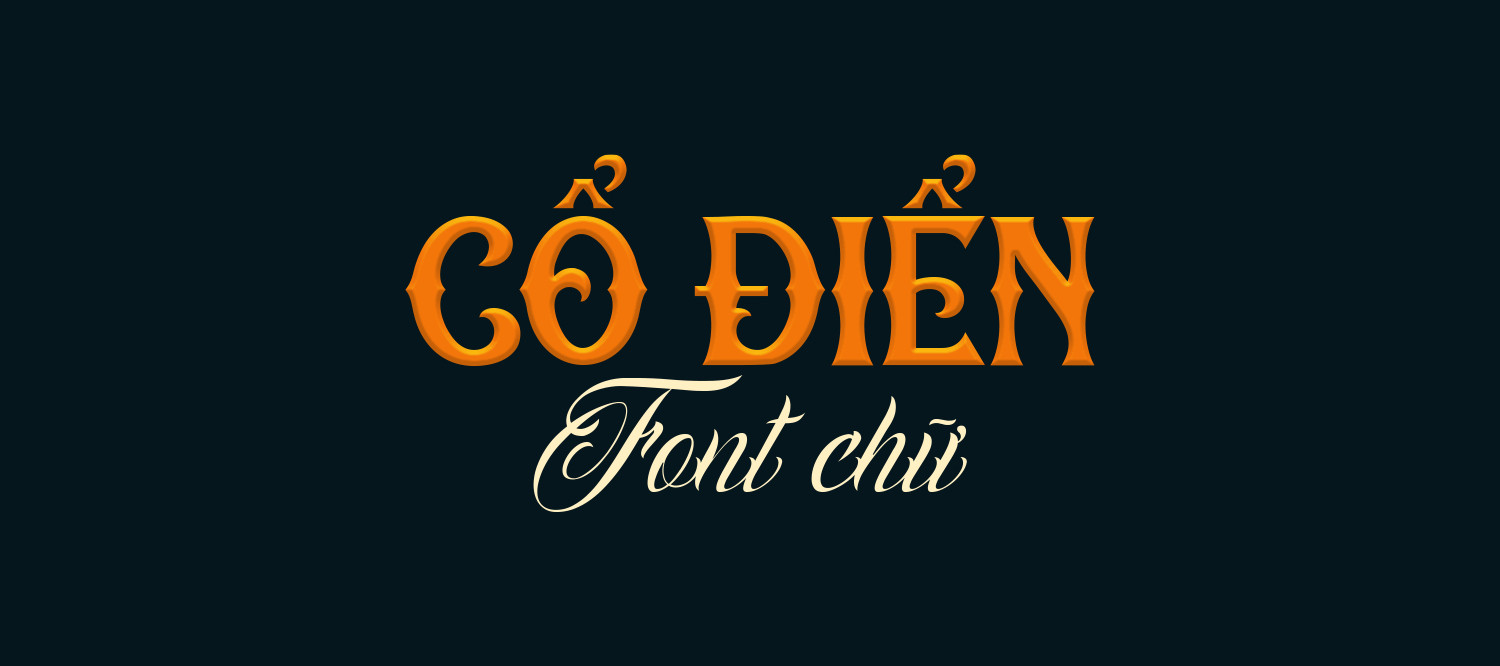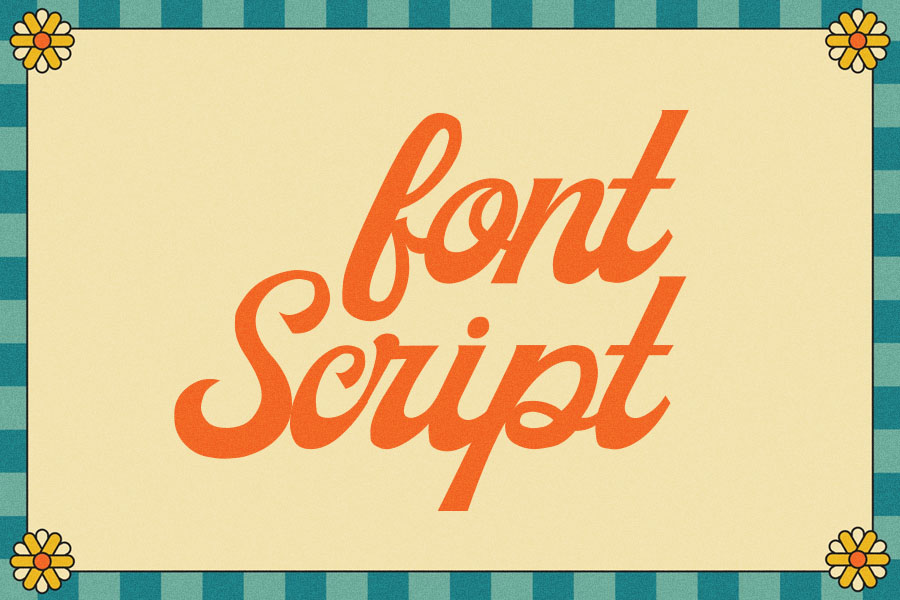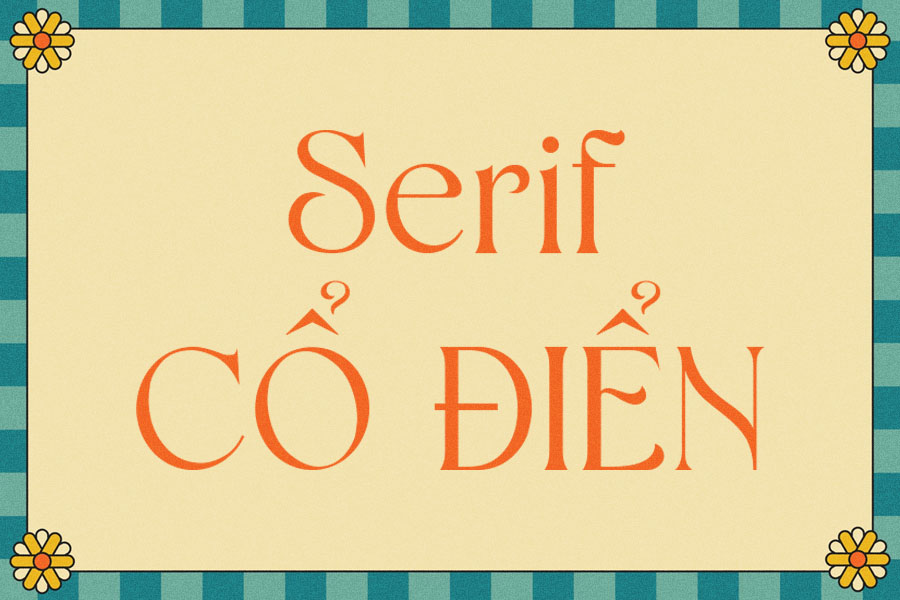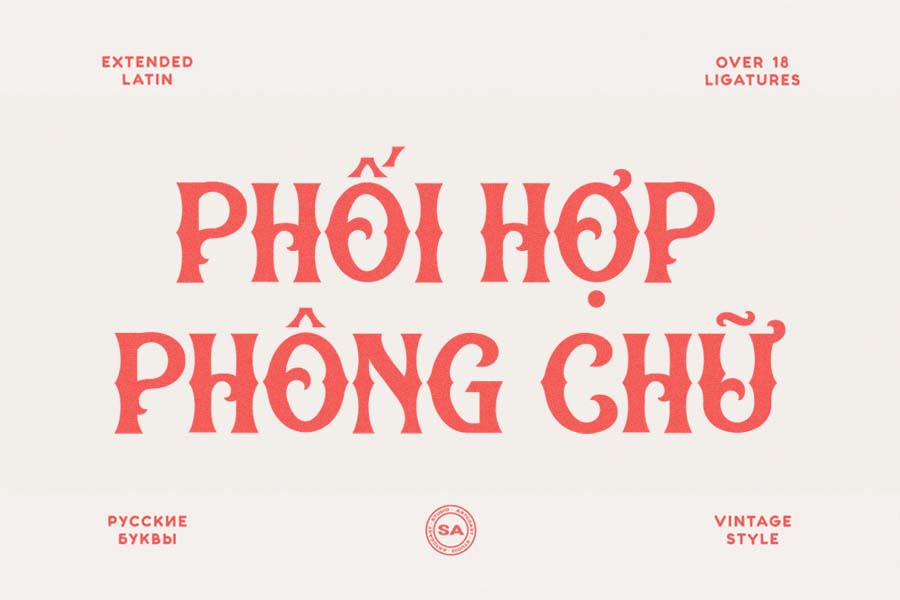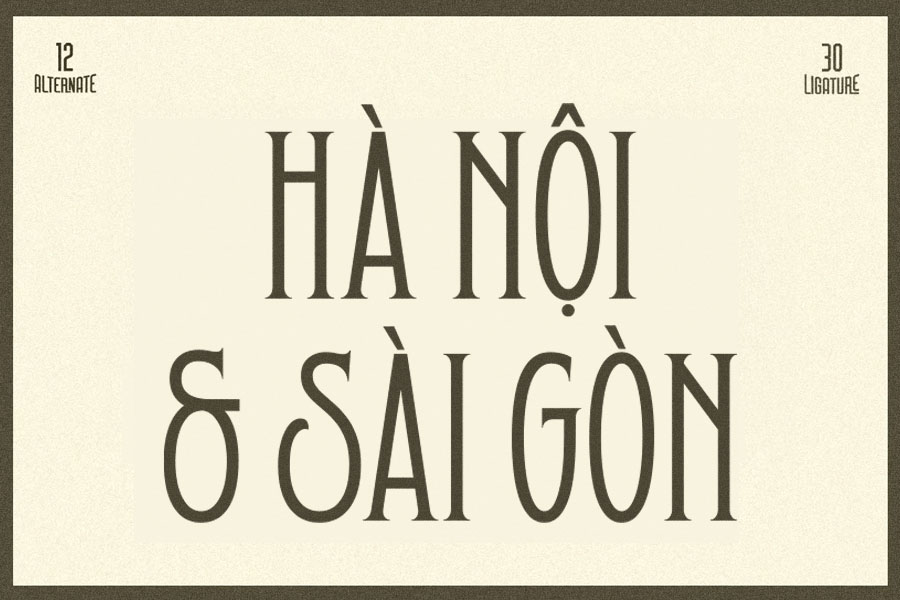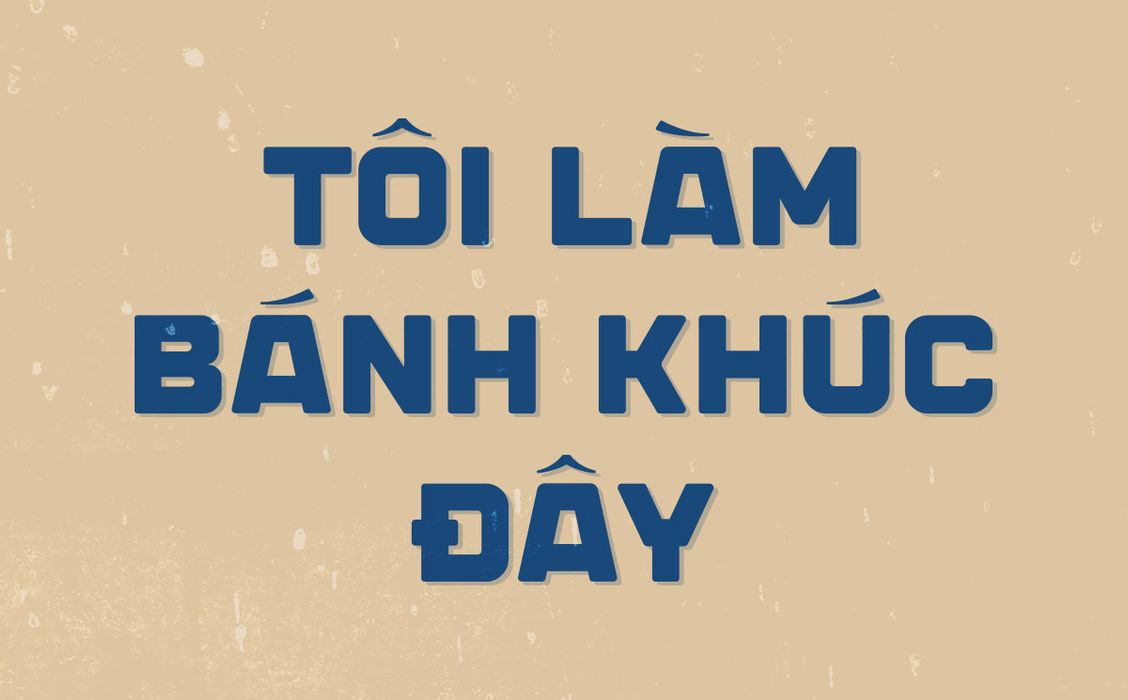
Bạn đang tìm kiếm những kiểu font chữ mang vẻ đẹp vượt thời gian, đậm chất hoài cổ, phù hợp cho các thiết kế logo, poster hay thiệp cưới mang phong cách sang trọng? Font chữ cổ điển chính là lựa chọn lý tưởng – không chỉ tạo chiều sâu cảm xúc mà còn giúp thiết kế nổi bật với phong cách đặc trưng.
Bài viết này sẽ giới thiệu 20 font chữ cổ điển Việt hóa đẹp nhất 2025, phân tích ứng dụng, định nghĩa rõ ràng các phong cách font cổ điển và hướng dẫn cách kết hợp tối ưu – giúp bạn sử dụng đúng font cho từng dự án sáng tạo.
Font chữ cổ điển (classic fonts) là những kiểu chữ mang đậm hơi thở truyền thống, được xây dựng dựa trên các nguyên tắc thiết kế kinh điển, thường xuất hiện trong các ấn phẩm in ấn, biển hiệu xưa hay logo thương hiệu lâu đời. Đặc điểm nổi bật của các font này là đường nét tinh tế, thanh lịch và mang đến cảm giác trang trọng. Một số font có chân (serif) rõ ràng, trong khi số khác mô phỏng nét viết tay mềm mại của thư pháp. Tỷ lệ chữ trong các font cổ điển thường được thiết kế cân đối, tạo nên cảm giác hài hòa, dễ đọc và dễ ghi nhớ. Khi nhìn vào một font cổ điển, người xem thường cảm nhận được nét trang nhã, hoài niệm – gợi nhớ về những thập niên đã qua, từ những năm 50–80 của thế kỷ trước.
Font cổ điển, retro và vintage là ba khái niệm thường bị nhầm lẫn vì đều mang sắc thái hoài cổ, nhưng thực tế mỗi loại lại mang một tinh thần thiết kế riêng biệt.
Font cổ điển (Classic fonts) mang phong cách tinh tế, thanh lịch, thường trung tính và có tính chuẩn mực cao. Những font này thường được dùng trong thiết kế sách, tạp chí, logo của các thương hiệu cao cấp hoặc các ấn phẩm mang tính trí tuệ và trang trọng.
Font retro lại thể hiện cá tính mạnh mẽ và vui tươi hơn. Chúng thường gợi nhớ đến các thiết kế mang âm hưởng của thập niên 70–90, với các đường nét nổi bật, màu sắc bắt mắt và cách điệu có phần nghịch ngợm, trẻ trung. Retro thường được ứng dụng nhiều trong các poster, biển hiệu hoặc thiết kế mang hơi hướng đại chúng và quảng cáo.
Font vintage là sự mô phỏng phong cách xưa cũ một cách rõ ràng hơn, đặc biệt tập trung vào cảm giác sờn cũ, thời gian mài mòn. Chúng thường xuất hiện trong các thiết kế lấy cảm hứng từ thời kỳ bao cấp, tem phiếu, biển hiệu quán ăn xưa hoặc các sản phẩm mang chất dân gian truyền thống. Vintage thiên về chất cảm xúc và chất liệu thị giác cũ kỹ hơn so với retro và classic.
Font serif cổ điển là kiểu chữ có chân (serif), tức là mỗi ký tự đều có những nét kéo dài nhỏ ở đầu hoặc chân chữ. Đây là dạng font phổ biến trong các ấn phẩm cổ điển như sách in, tạp chí, báo chí thời xưa bởi sự dễ đọc, nhịp điệu ổn định và vẻ ngoài trang trọng, trí tuệ.
Font script cổ điển lấy cảm hứng từ chữ viết tay bằng bút máy hoặc thư pháp. Các ký tự thường nối liền nhau, tạo dòng chảy mượt mà và giàu cảm xúc thị giác. Đây là lựa chọn hàng đầu trong các thiết kế cần sự nhẹ nhàng, tình cảm và mang hơi hướng cá nhân.
Font retro và vintage là dòng font mô phỏng lại các kiểu chữ từ thập niên 50–90 hoặc thậm chí thời bao cấp ở Việt Nam. Chúng thường mang vẻ ngoài thô ráp, sờn cũ hoặc có các chi tiết thiết kế "lỗi thời có chủ đích" để gợi lại cảm xúc hoài niệm. Kiểu font này rất phổ biến trong các thiết kế có yếu tố văn hóa đại chúng, nghệ thuật đường phố hoặc mang màu sắc dân gian.
1. Font chữ cổ điển TH Hustle Culture Việt hóa
TH Hustle Culture là một font serif cổ điển mang hơi hướng phương Tây, nổi bật với các đường nét dày, chắc chắn và gãy gọn. Font gợi cảm giác quyền lực, cổ kính, và đặc biệt thích hợp trong các thiết kế logo sang trọng, poster phim, bìa sách cổ điển hoặc thương hiệu di sản. Cách phối hợp giữa nét hiện đại và cổ điển trong bộ font giúp người dùng dễ dàng sử dụng cho cả mục đích thương mại lẫn nghệ thuật.
2. Font chữ cổ điển TH Wible Town Việt hóa
TH Wible Town là font serif mang đậm tinh thần cổ điển của biển hiệu Việt Nam thập niên 60–80. Với các đường nét rõ ràng, mạnh mẽ và cứng cáp, font mang đến cảm giác của thời kỳ báo chí in ấn thủ công. Đây là lựa chọn hoàn hảo cho các thiết kế bao bì, bìa sách, poster mang hơi thở tem phiếu hoặc phong cách "Sài Gòn xưa". Font hỗ trợ đầy đủ tiếng Việt, dễ đọc và in ấn rõ nét.
3. Font chữ cổ điển TH Hansel Rough Việt hóa
TH Hansel Rough thuộc nhóm font serif cổ điển với phong cách thô ráp, mô phỏng hiệu ứng in mòn thời xưa. Các nét chữ có sự bất đều nhẹ, tạo nên vẻ thủ công, gần gũi và hoài niệm. Font rất thích hợp để sử dụng cho các thiết kế poster phim cổ, bìa sổ tay, nhãn sản phẩm thủ công hoặc bao bì mang phong cách rustic. Nếu bạn đang tìm một kiểu chữ cổ điển nhưng không quá bóng bẩy – đây là lựa chọn lý tưởng.
4. Font chữ cổ điển MJ Bygonest Việt hóa
MJ Bygonest là kiểu font cổ điển mang cảm hứng từ thời kỳ bao cấp ở Việt Nam. Với thiết kế block to, dày và chắc chắn, font gợi lại hình ảnh các tem phiếu, biển hiệu, và tài liệu tuyên truyền xưa. Đây là font lý tưởng cho các thiết kế muốn tái hiện chất retro Việt đậm nét như: poster thời bao cấp, bao bì bánh kẹo xưa, hoặc các sản phẩm mang thông điệp văn hóa hoài cổ.
Font cổ điển và font serif có giống nhau? → Không hoàn toàn, serif là một nhóm nhỏ trong font cổ điển.
Có nên dùng nhiều font cổ điển trong cùng thiết kế? → Nên giới hạn 1–2 font.
Font chữ cổ điển không chỉ là di sản thiết kế – mà còn là nguồn cảm hứng. Dù bạn thiết kế cho một thương hiệu sang trọng, một poster phim hoài cổ, hay chỉ đơn giản là muốn tăng chiều sâu cho tác phẩm hãy cân nhắc sử dụng font cổ điển.